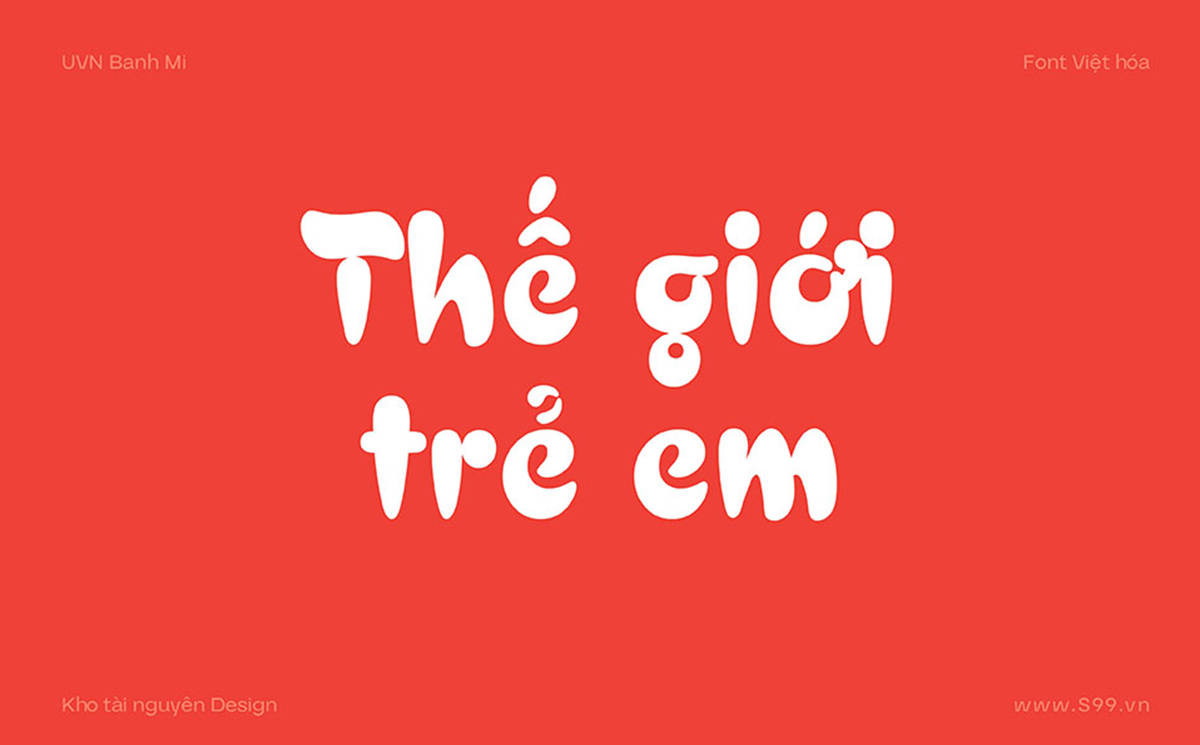
Phông chữ tiếng Việt miễn phí UVN Bánh Mì
Phông chữ tiếng Việt miễn phí UVN Bánh Mì là một trong những bộ font mang đậm phong cách hoài cổ, tái hiện hoàn hảo nét văn hóa ẩm thực đặc trưng và nghệ thuật vẽ bảng hiệu xưa của Việt Nam. Được thiết kế tỉ mỉ với đường nét mộc mạc nhưng vô cùng tinh tế, font chữ này đem lại cảm giác thân thuộc, gần gũi và đầy tính sáng tạo cho mọi tác phẩm đồ họa. Đây chính là lựa chọn lý tưởng dành cho các nhà thiết kế, chủ cửa hàng ẩm thực hay bất kỳ ai đang tìm kiếm một phông chữ Việt hóa ấn tượng và hoàn toàn miễn phí.
Khám Phá Phông Chữ Tiếng Việt Miễn Phí UVN Bánh Mì – Lựa Chọn Hoàn Hảo Cho Thiết Kế Retro Độc Đáo
Xu hướng thiết kế mang phong cách Retro và Vintage đang quay trở lại mạnh mẽ trong những năm gần đây, kéo theo sự lên ngôi của các bộ font chữ mang hơi hướng hoài niệm. Trong số đó, phông chữ tiếng Việt miễn phí UVN Bánh Mì nổi lên như một điểm sáng nghệ thuật, gợi nhớ về những bảng hiệu vẽ tay dọc các con phố Sài Gòn xưa hay những tiệm bánh mì truyền thống rực rỡ sắc màu.
Bộ phông chữ này không chỉ đơn thuần là công cụ thể hiện văn bản, mà còn mang trong mình linh hồn của một nét văn hóa Việt Nam bình dị. Việc sử dụng phông chữ tiếng Việt miễn phí UVN Bánh Mì giúp các nhà thiết kế nhanh chóng truyền tải thông điệp về sự mộc mạc, chân thành và nét đẹp thời gian đến với khách hàng. Dù bạn đang triển khai dự án nhận diện thương hiệu cho quán ăn, quán cà phê hay tạo các ấn phẩm truyền thông trên mạng xã hội, font chữ này đều có thể đáp ứng một cách trọn vẹn và chuyên nghiệp.
1. Phong cách thiết kế Retro đậm chất văn hóa Việt Nam
Phông chữ UVN Bánh Mì sở hữu những nét vẽ dày, chắc chắn kết hợp với các đường cong uốn lượn tự nhiên, gợi liên tưởng trực tiếp đến nghệ thuật vẽ chữ thủ công trên các bảng hiệu quảng cáo thập niên 70 – 80 tại Việt Nam. Sự mộc mạc trong từng nét chữ mang lại cảm giác hoài cổ, ấm áp và vô cùng gần gũi. Đây là giải pháp hoàn hảo để tạo nên điểm nhấn thị giác khác biệt, giúp thương hiệu của bạn nổi bật giữa hàng loạt các thiết kế hiện đại mang tính rập khuôn.
2. Hỗ trợ trọn bộ ký tự Tiếng Việt chuẩn mực và sắc nét
Một trong những ưu điểm lớn nhất của bộ font này chính là khả năng hiển thị tiếng Việt hoàn hảo. Được tối ưu hóa cho hệ thống dấu thanh tiếng Việt, phông chữ tiếng Việt miễn phí UVN Bánh Mì khắc phục hoàn toàn lỗi dính dấu, mất dấu hay các khoảng cách bất hợp lý giữa các ký tự – vấn đề thường gặp ở các font chữ nước ngoài. Các dấu hỏi, ngã, sắc, huyền, nặng cùng các ký tự đặc trưng như ê, ơ, ư đều được tạo hình cân đối, giúp văn bản duy trì tính thẩm mỹ cao nhất.
3. Tính ứng dụng đa dạng trong nhiều lĩnh vực thiết kế
Không bị giới hạn trong phạm vi các cửa hàng bánh mì hay ẩm thực đường phố, phông chữ UVN Bánh Mì có tính linh hoạt rất cao. Bạn có thể sử dụng bộ font này cho nhiều loại sản phẩm sáng tạo khác nhau như:
• Thiết kế logo, bảng hiệu cho quán cà phê, tiệm bánh, nhà hàng phong cách cổ điển.
• Làm bao bì sản phẩm, tem nhãn bao bì mang đậm phong cách truyền thống.
• Thiết kế poster, banner quảng cáo, thiệp mời, bìa sách và ấn phẩm truyền thông.
• Tạo hình ảnh nội dung ấn tượng trên các nền tảng mạng xã hội như Facebook, Instagram, TikTok.
Bí Quyết Phối Hợp Font UVN Bánh Mì Để Tạo Ấn Phẩm Đồ Họa Ấn Tượng
Để phát huy tối đa vẻ đẹp của phông chữ tiếng Việt miễn phí UVN Bánh Mì trong tác phẩm của mình, bạn có thể áp dụng một số nguyên tắc phối chữ và phối màu sau đây:
1. Kế thừa bảng màu hoài cổ: Hãy kết hợp phông chữ này với các gam màu Retro đặc trưng như vàng nghệ, đỏ gạch, xanh đậm hoặc nâu đất để làm tăng tính thẩm mỹ cổ điển cho thiết kế.
2. Sử dụng làm tiêu đề chính (Headline): Do có đường nét khá dày và ấn tượng, font UVN Bánh Mì phát huy hiệu quả tốt nhất khi dùng cho các tiêu đề lớn, banner quảng cáo hoặc tên thương hiệu. Tránh dùng font này cho các đoạn văn bản dài (body text) để đảm bảo độ dễ đọc.
3. Phối hợp với font Sans-serif hiện đại: Kết hợp tiêu đề sử dụng UVN Bánh Mì với phần nội dung sử dụng các font không chân tối giản (như Roboto, Open Sans, Montserrat) sẽ tạo ra sự cân bằng hoàn hảo giữa nét cổ điển và tính hiện đại.
Như vậy, font Bánh Mì Việt hóa là một sự kết hợp hoàn hảo giữa thẩm mỹ, tính tiện dụng và sự gần gũi. Font này không chỉ là công cụ thiết kế mà còn là đại diện cho sự sáng tạo và tinh thần văn hóa Việt Nam, giúp các dự án thiết kế của bạn trở nên nổi bật và đầy ấn tượng.